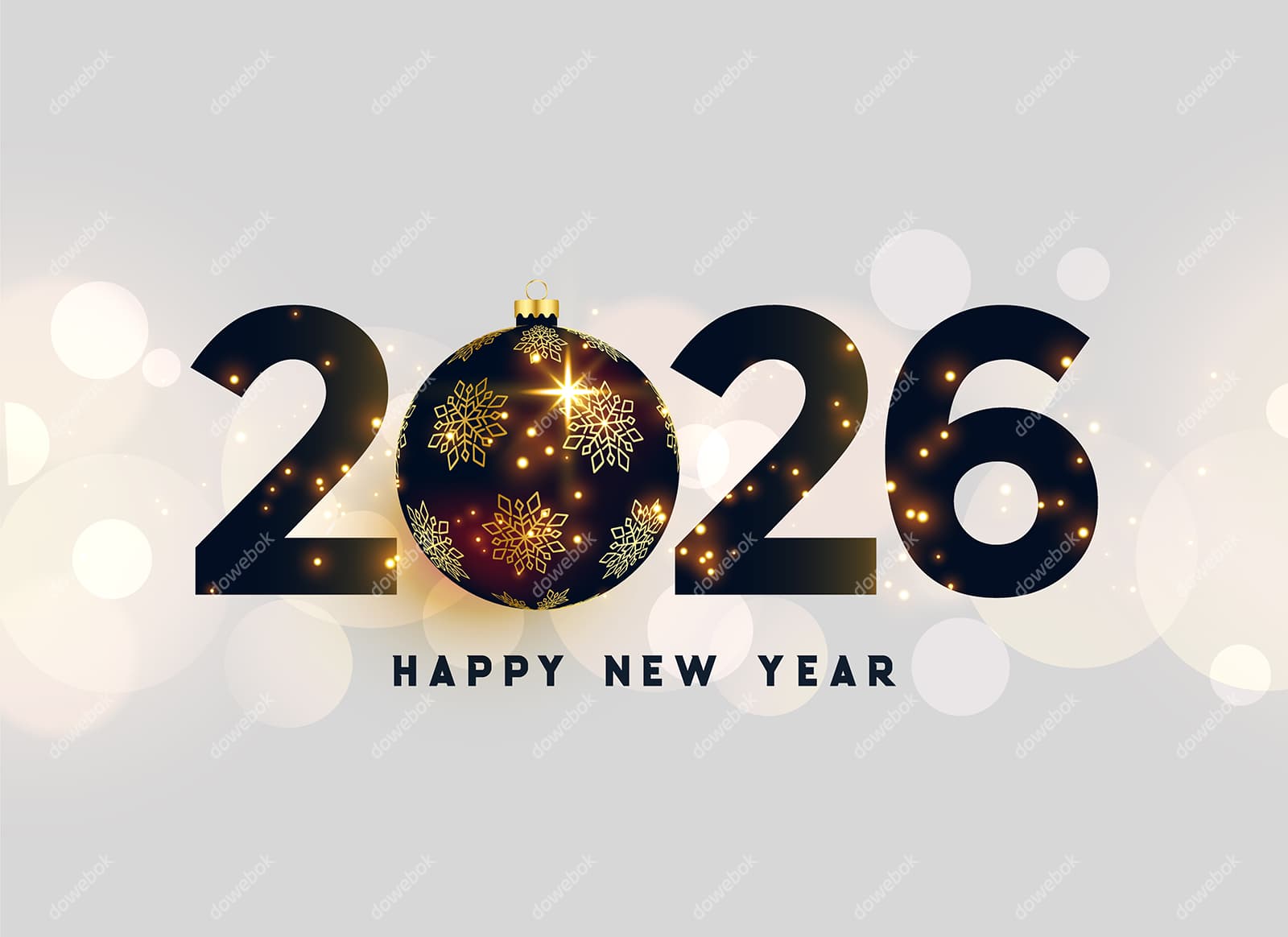
这是一款圣诞装饰球设计 2026 新年快乐矢量素材,浅灰背景衬着柔焦光斑,营造柔和氛围。黑色 “2026” 字体简洁大气,数字 “0” 替换为黑金雪花纹装饰球,缀着星光亮点,精致亮眼。下方配简约黑体 “Happy New Year”,整体以低饱和色调 + 轻奢装饰,既显节日温馨,又透出雅致质感,契合跨年的温柔喜庆。